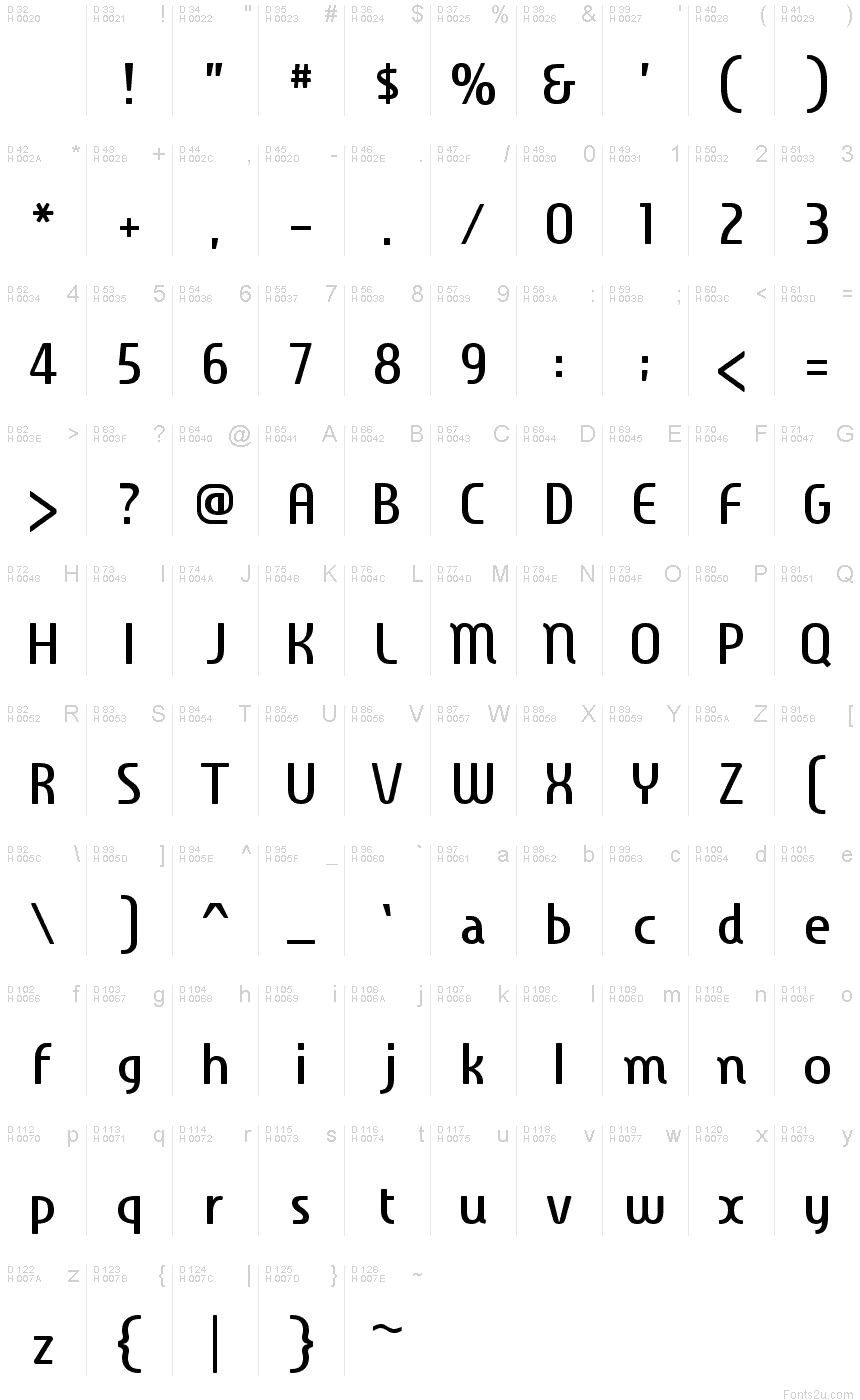
Familian Elder von Hideki Katayama ist eine moderne, kostenlose Display-Sans-Schrift mit einer sanften, leicht retro-inspirierten Note. Die Buchstaben verbinden breite, abgerundete Striche mit einigen scharf zulaufenden Verbindungen und markanten Details. Dadurch wirkt die Schrift auf den ersten Blick freundlich, besitzt aber gleichzeitig einen einprägsamen, unkonventionellen Charakter.
Diese Balance eignet sich perfekt für Branding, Café-Speisekarten, Plakat-Überschriften, Verpackungsdesign, Magazin-Cover und kurze Web-Headlines, wenn eine kostenlose Schriftart mehr Persönlichkeit braucht als ein schlichtes geometrisches Sans-Serif. Sie entfaltet ihre beste Wirkung in kurzen Display-Anwendungen, da die schwungvollen Kurven und eigenwilligen Bogenformen selbst kurzen Wörtern eine unverwechselbare Silhouette verleihen.